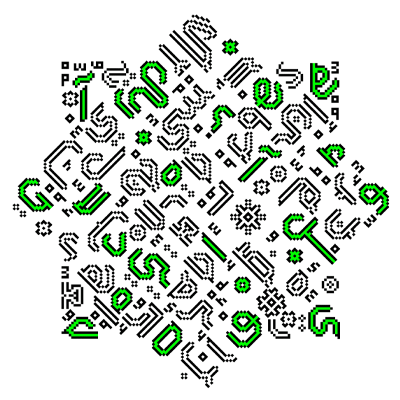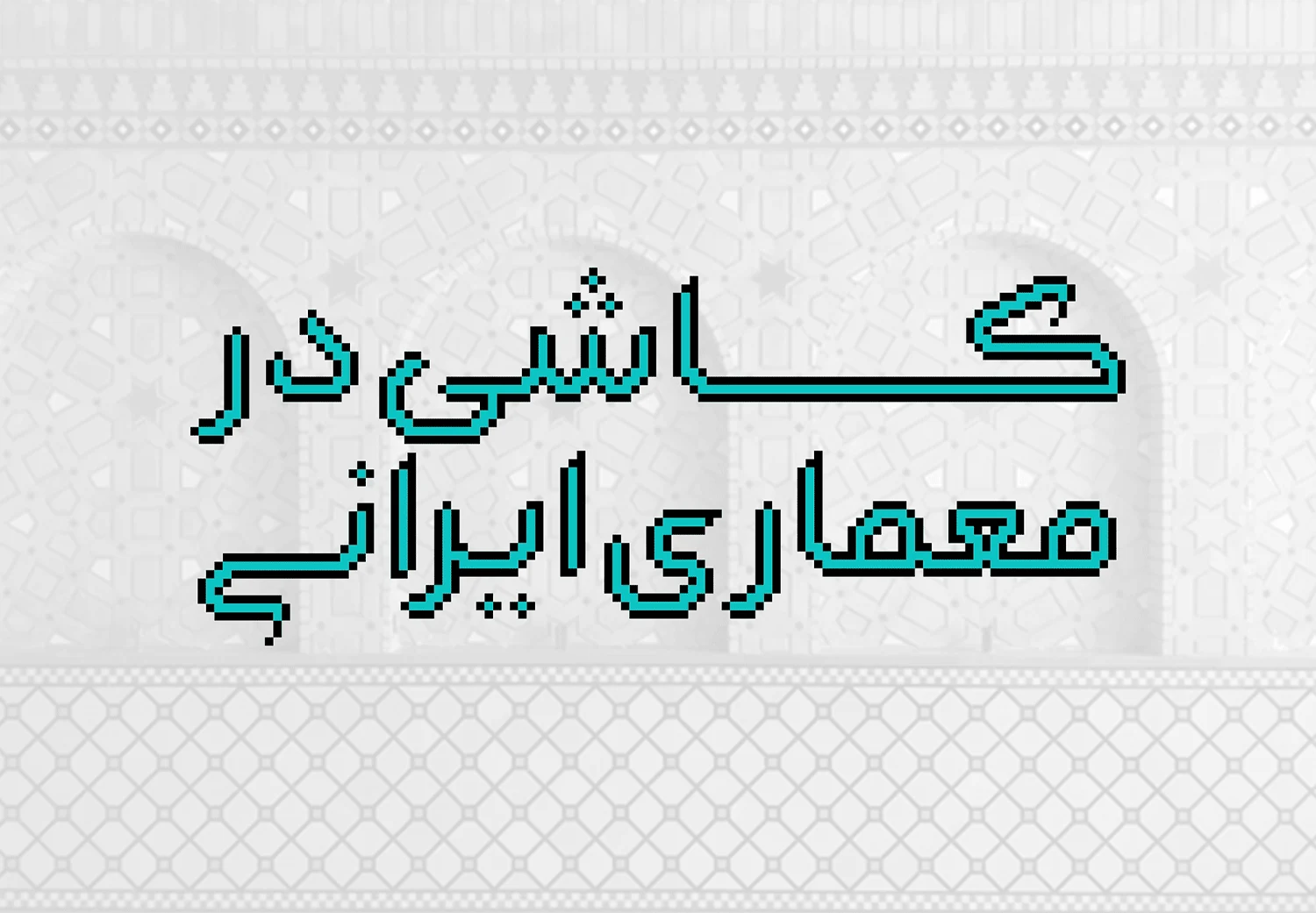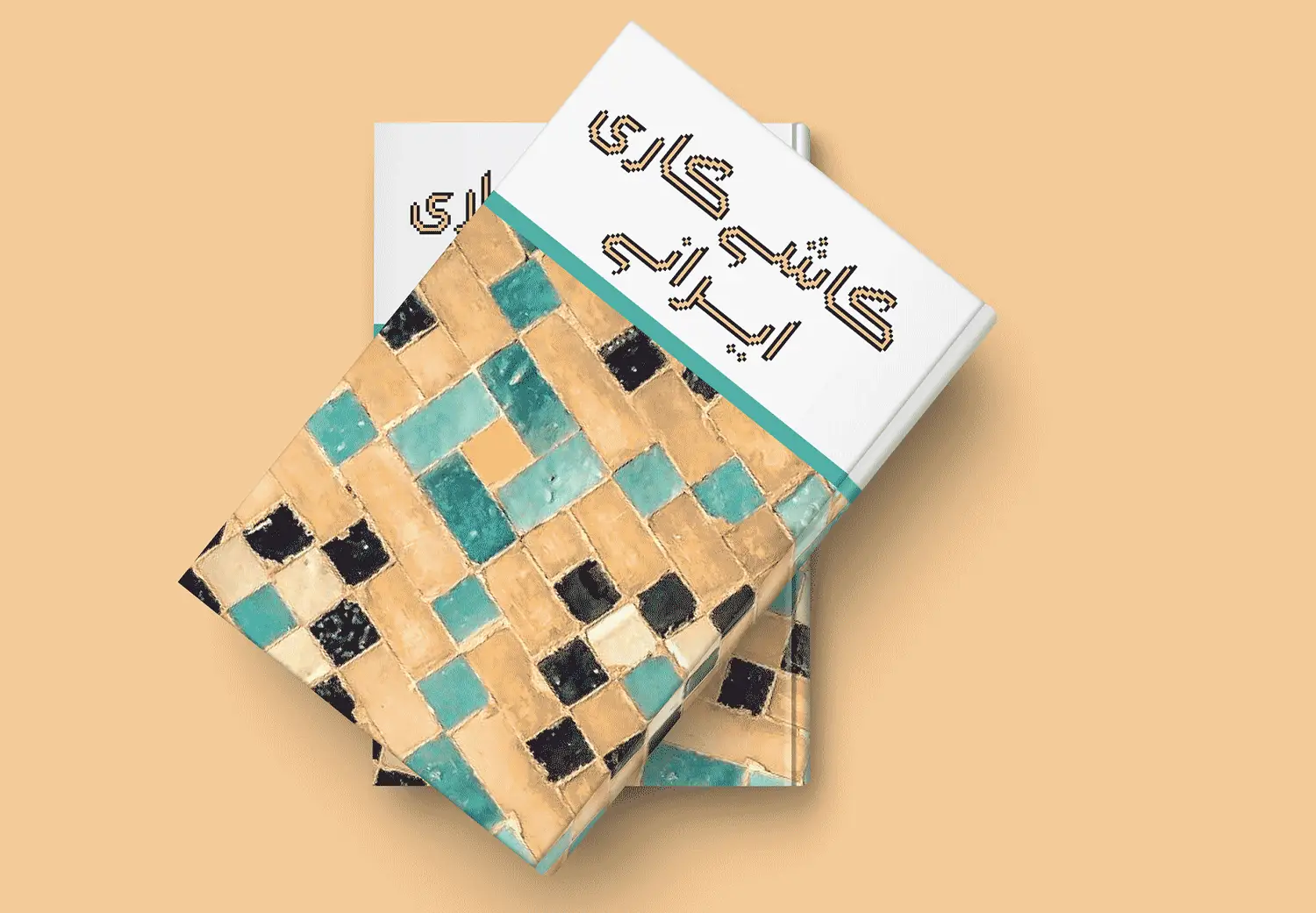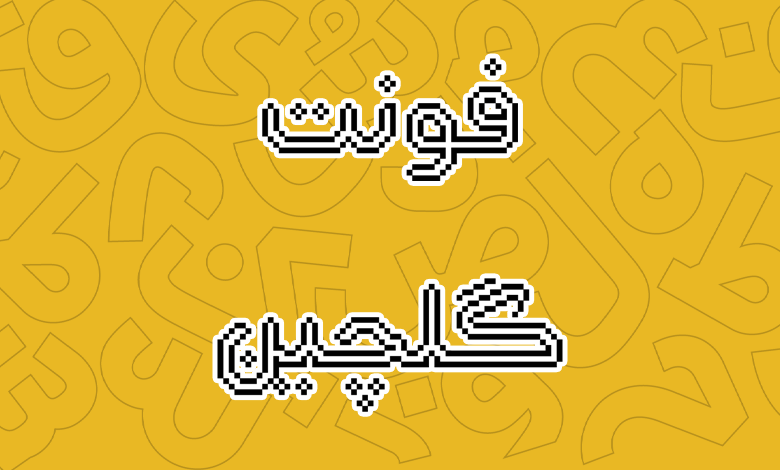
فونت گلچین (Golchin)
فونت گلچین (به انگلیسی: Golchin) جزو اولین فونت رنگی فارسی است که امکان تایپ کلمات را به صورت رنگی در اختیار شما قرار خواهد داد. این فونت برگرفته از خط نسخ و با الهام از خط کوفی بنایی ساقهگنبدی که بیشتر در آثار تاریخی ایرانی آنها را در طرحهای کاشیکاری دیدهایم طراحی شده است.
وحید یعقوبلو این قلم تزئینی را با الهام از طرح کاشی روی گنبدها، سردرها و گاهی کتیبه ایوانها که در آثار تاریخی شهرهای مختلف ایران دیده میشود و در سایر کشورها همچون افغانستان نیز بر مزار بزرگانی چون خواجه عبدالله انصاری کار شده ساخته است. امین عابدی نیز توسعه نرمافزاری این قلم را برای استفاده در انواع سیستمعامل فراهم نموده است.
در ادامه این نوشته از سایت فونتچی به نقد و بررسی کامل فونت گلچین خواهیم پرداخت؛ قلمی که با الهام از چند نوع ساختار خوشنویسی ایرانی و برگرفته از آثاری که نمایانگر تاریخ ایرانی هستند ساخته شده است.
این قلم اصل و پایهاش خطوطی چون کوفی، ثلث، و بعضا سایر اقلام خوشنویسی است که بر پایهی شبکهای شطرنجی با ساختار پیکسلی نقش میبندد و قواعد ترسیم آن با سایر نمونهها کمی متفاوت است.
ساختار قلم درست همانند چینش کاشیها بر روی گنبدها، سردر ایوانها و کتیبهها صورت گرفته است که با قرار گرفتن نقاط در کنار یکدیگر ساختار کلی قلم را تشکیل داده است.
سبک طراحی و وزن فونت گلچین
فونت گلچین شکل امروزی شده و کاربری خط ساقه گنبدی است که در گذشته از آن برای طرح کاشیکاری بر روی گنبدها بسیار استفاده میشده است.
خط ساقه گنبدی نوعی برخورد مینیمال با طراحی حروف است. طراحی حروف پیچیده فارسی با منحنیهای زیاد در یک شبکه محدود شطرنجی کاری بسیار مشکل است. وحید یعقوبلو در طراحی تایپفیس گلچین محدودیتهای بیشتری نیز برای رعایت سیستم حروفچینی در فونت داشته است.
با حل کردن چنین ساختارهای پیچیدهای در قالب یک قلم نرمافزاری در نهایت فونت گلچین شکل گرفته است که میتوانید آن را در ۳ وزن مختلف شامل نازک (Thin)، معمولی (Regular) و بولد (Bold) دریافت کنید.
پشتیبانی از دو زبان فارسی و عربی
فونت گلچین از زبان فارسی پشتیبانی کاملی دارد. الهام گرفتن این قلم بر اساس نقوش روی گنبدهای تاریخی ایرانی بوده است که با ترکیبی از ساختارهای نسخ، ثلث و کوفی ایجاد شده است. در تمامی وزنها و استایلها چینش پیکسلی فونت وجود دارد با این تفاوت که وزن معمولی ساختاری اینلاین دارد.
چنین ساختار درون خطی را پیش از این در قلمهایی مثل فونت ارژن، فونت ابتکار و فونت همتا معرفی کردهایم. برخی دیگر قلمها نظیر فونت سپید نیز دارای یک وزن با همین طراحی هستند.
نسخه عربی فونت گلچین نیز بر اساس رسمخط فارسی شگل گرفته است و همانطور که میدانید ارتباط فرهنگی بین فارسی و عربی در نقوش اسلامی همواره در آثار تاریخی ما وجود داشته است. برای زبان عربی نیز جدای از حروف، اعراب در این قلم پیاده سازی شده و تفاوتهایی که در برخی حروف مثل «ک، و، ه، ی» که از نظر نوشتاری دارای نقطه یا همزه هستند پیاده سازی شده است.
پشتیبانی این قلم برای اعداد نیز مطابق استاندارد هر زبان درنظر گرفته شده است. اعدادی مثل «۴۵۶» در زبان عربی که در مقایسه با اعداد فارسی «۴۵۶» ساختار و شکل متفاوتی دارند در این قلم پیادهسازی شده است.
اما در این فونت خبری از پشتیبانی برای زبان لاتین وجود ندارد و برای کارهایی گرافیکی که منطبق بر دو زبان فارسی و لاتین باشند، باید از قلم دیگری که ساختاری نزدیک به این قلم دارد استفاده کنید.
فونت رنگی با ۵ رنگ متنوع
فونت گلچین اولین فونت رنگی فارسی است که امکان تایپ حروف را بدون نیاز به انتخاب رنگ از طریق نرمافزار در ۵ رنگ مختلف در اختیارتان قرار خواهد داد که این رنگها مشابه به تصویر زیر هستند.
رنگهای آبی (نیلی)، سبز، نارنجی، زرد و خاکستری برای این قلم درنظر گرفته شده که میتوانید در وزن Regular که طراحی درون خطی (اینلاین) دارد از آنها استفاده کنید.
دارای ترکیبات و حروف جایگزین
ویژگی دیگر فونت گلچین پشتیبانی از ترکیبات و حروف خاص است که امکان تایپ کلمات را در چند شکل مختلف فراهم میکند. برای مثال همانطور که در تصویر زیر مشاهده میکنید، حروف و ترکیبات «ک، ـی، ی» امکان تایپ در چند شکل مختلف را دارند که میتواند به زیباتر کردن و جلب توجه برخی کلمات با تایپ متفاوت به ما کمک کند.
این قلم مناسب متنهای طولانی نبوده و بهتر است از آن برای متن کوتاه و عناوین استفاده کنید. یکی از بیشترین کاربردهای این فونت تبلیغات و صنعت مطبوعات است که میتوان برای طراحی جلد روی کتب یا هویت بصری برای کارهای فرهنگی و هنری از آن استفاده کرد.